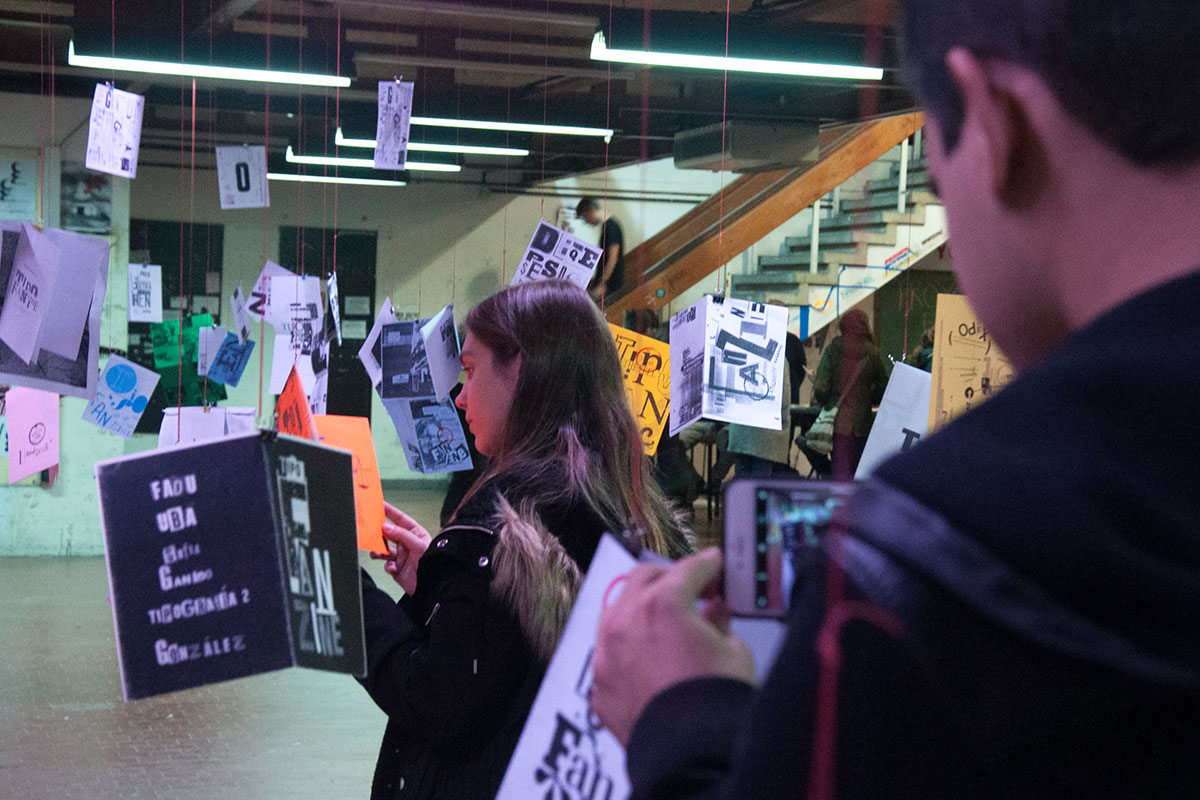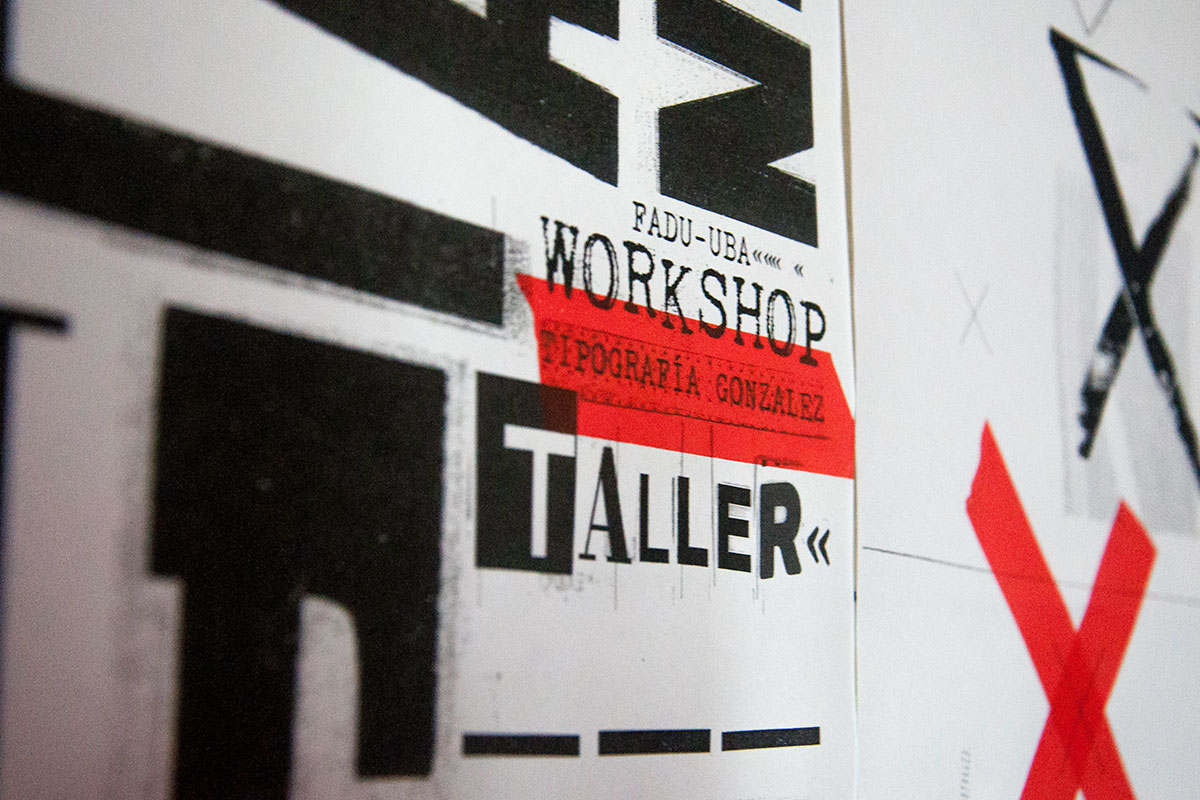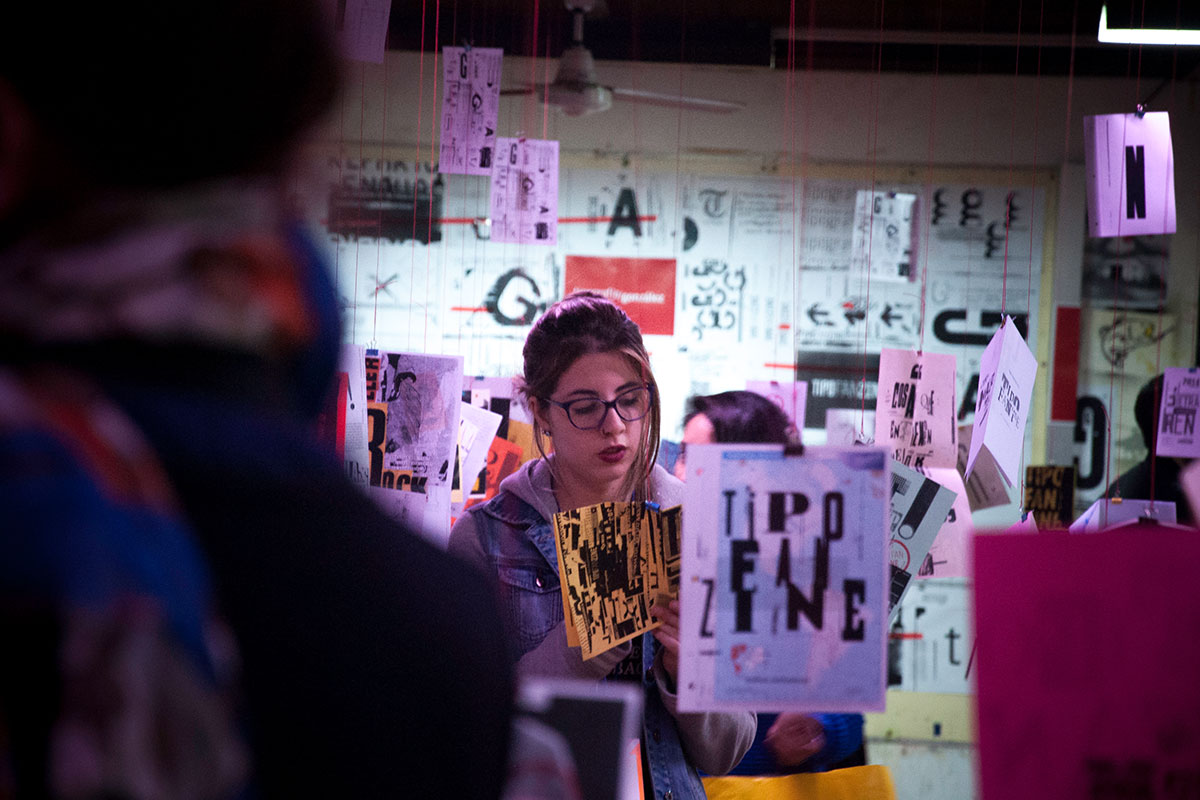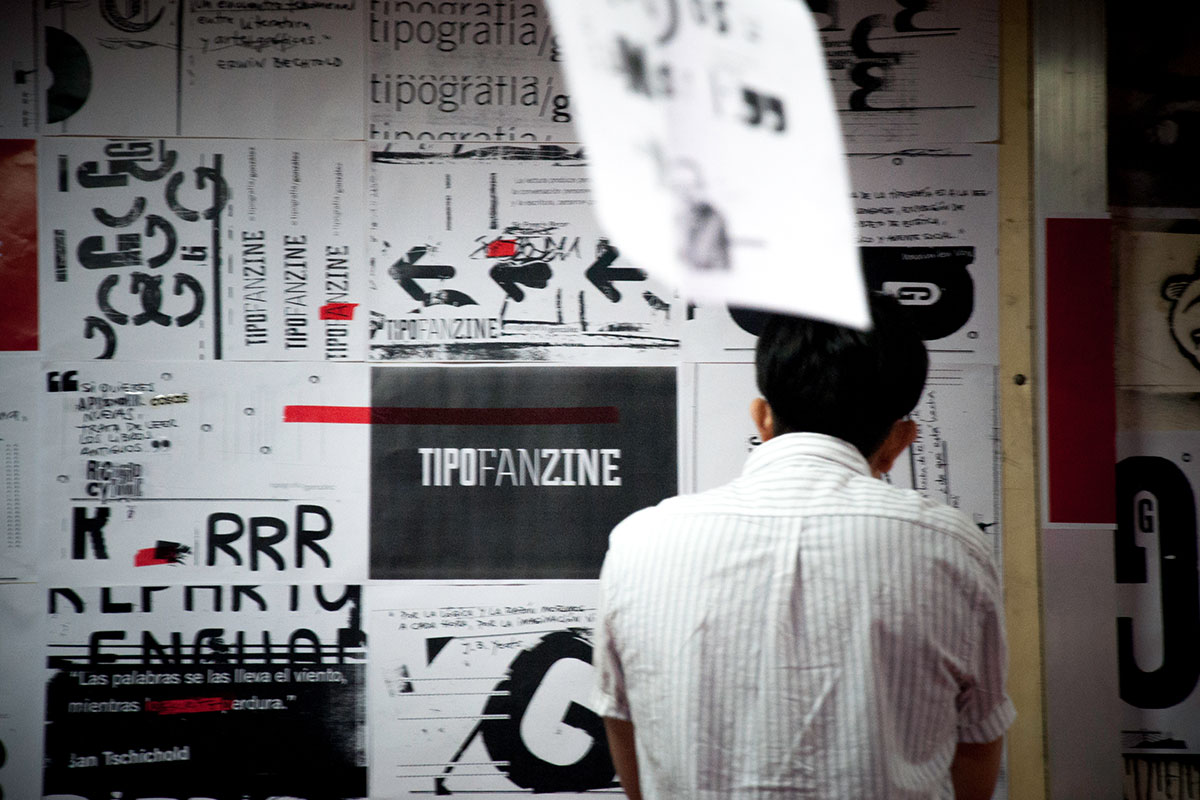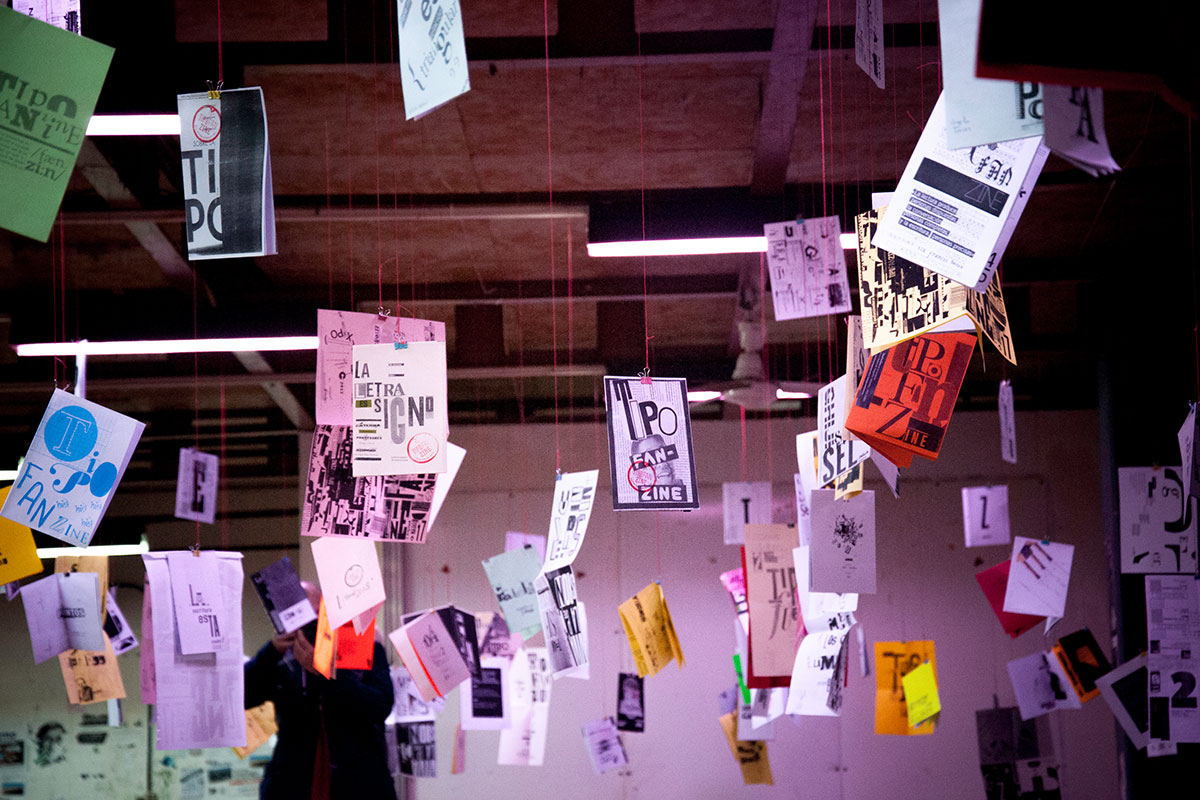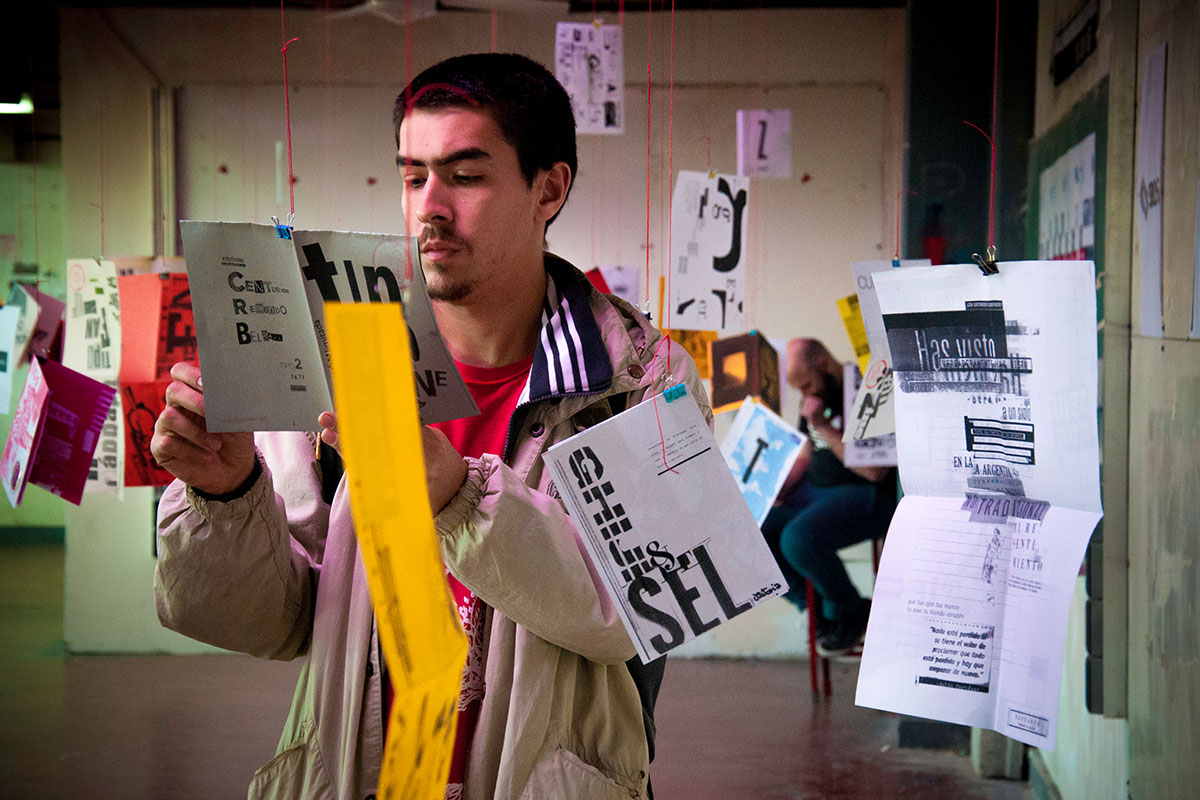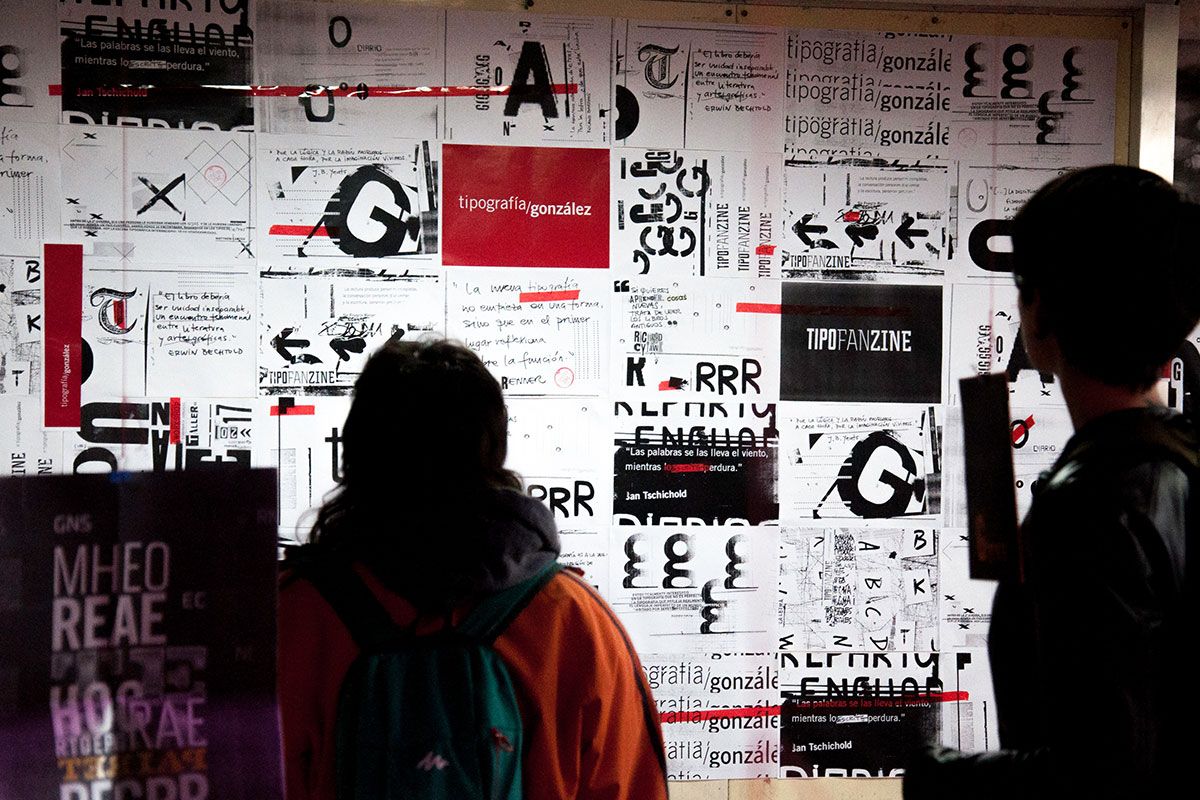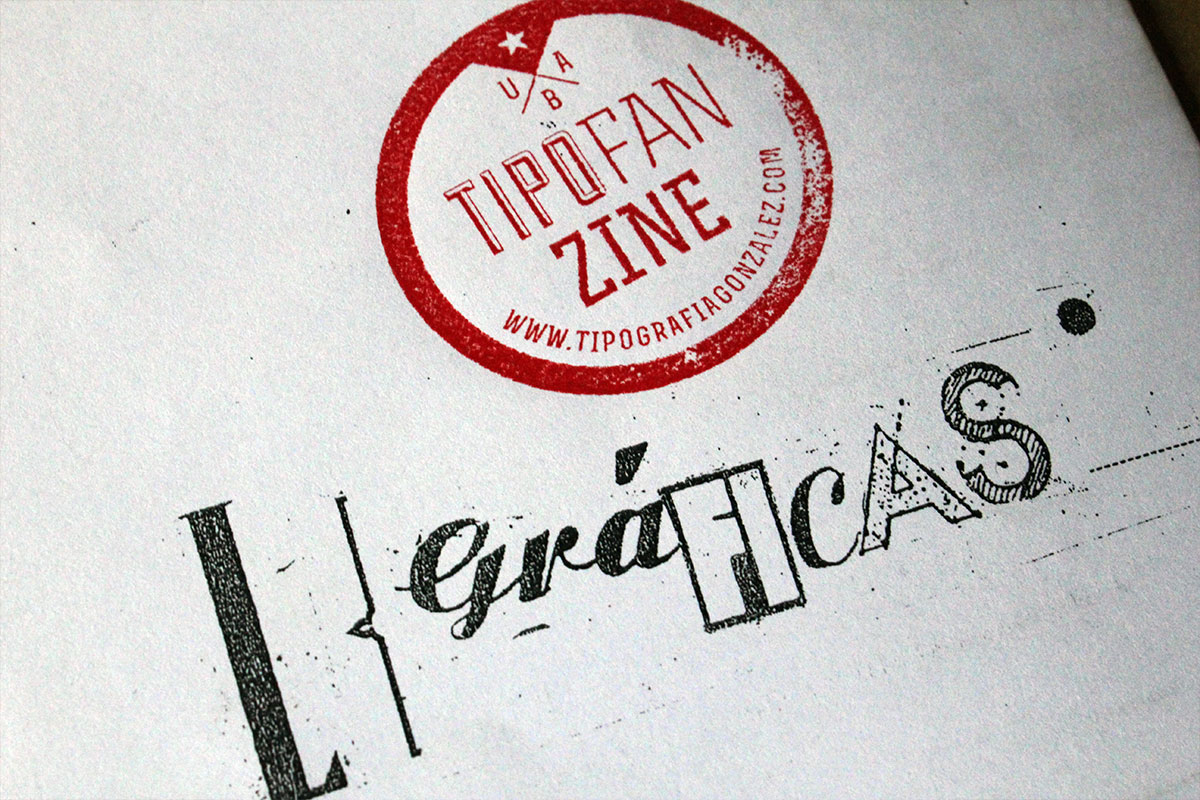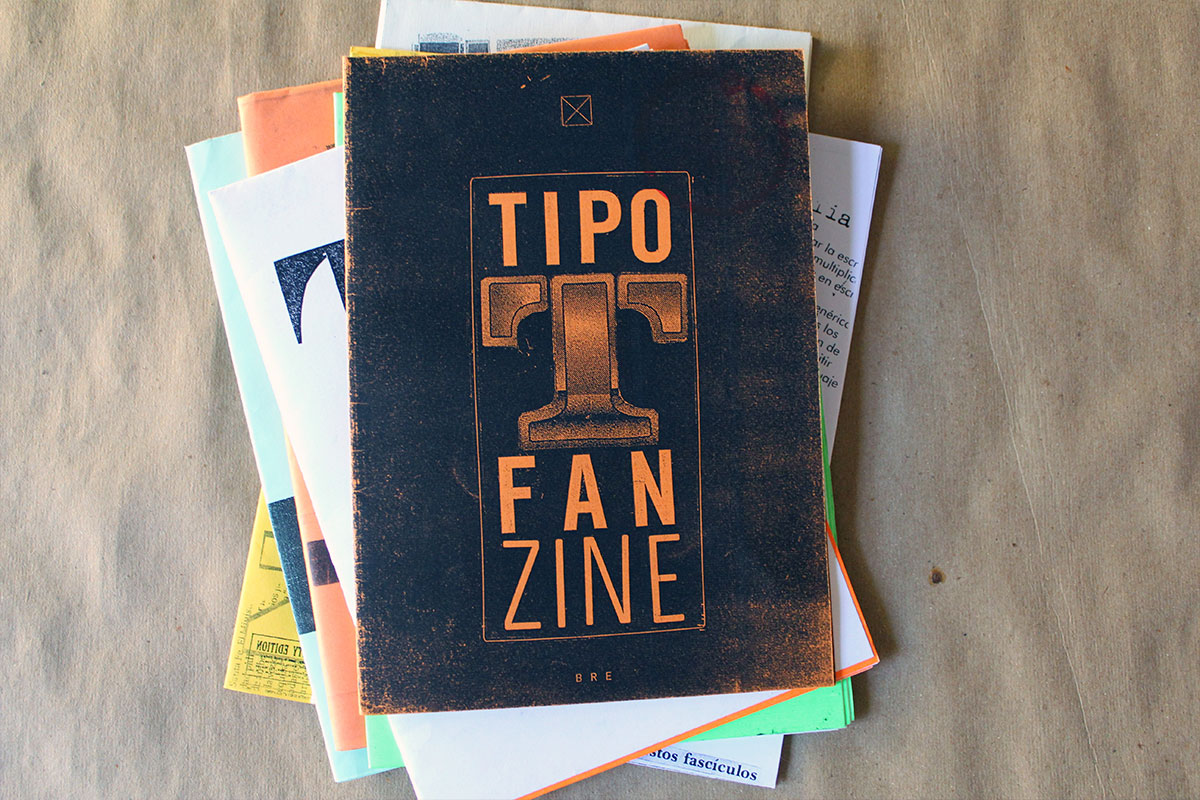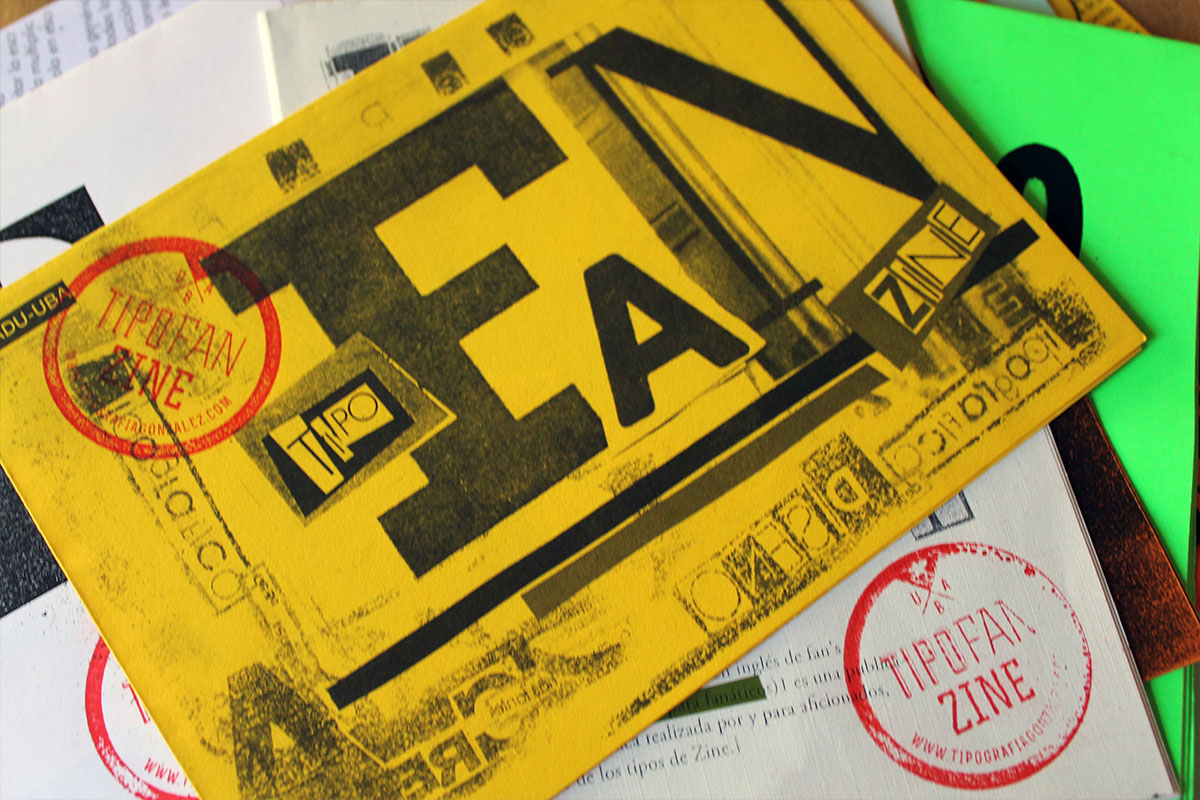
TipoFanZine
Este trabajo nos propone la realización de un fanzine tipográfico a partir de la observación y el análisis de distintos tipos de publicaciones de corte experimental.
Con el objetivo de explorar el uso de la tipografía y su relación con la imagen en una publicación no convencional, los estudiantes emplean la técnica del collage y la fotocopia para la realización colectiva de un proyecto.